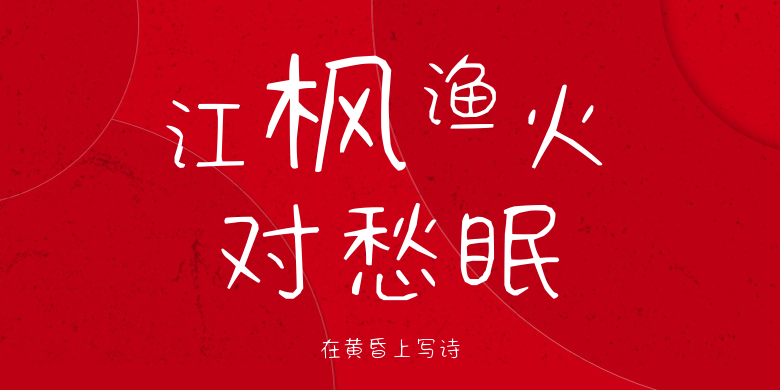
在黄昏上写诗
在黄昏上写诗,这款字体结构工整、笔画清晰,兼顾美观与易读性,适用于标题、正文、海报、包装、LOGO 等多种场景。字形优雅稳定,风格百搭耐看,适配日常排版与创意设计,让文字呈现更舒适、更具质感。在黄昏上写诗一笔一画,皆是细节,以均衡的比例、流畅的线条打造舒适视觉体验,字形端正大气,风格简约现代。无论是商业设计、品牌宣传还是日常排版,都能轻松驾驭,让文字更有格调与力量。在黄昏上写诗字体下载。